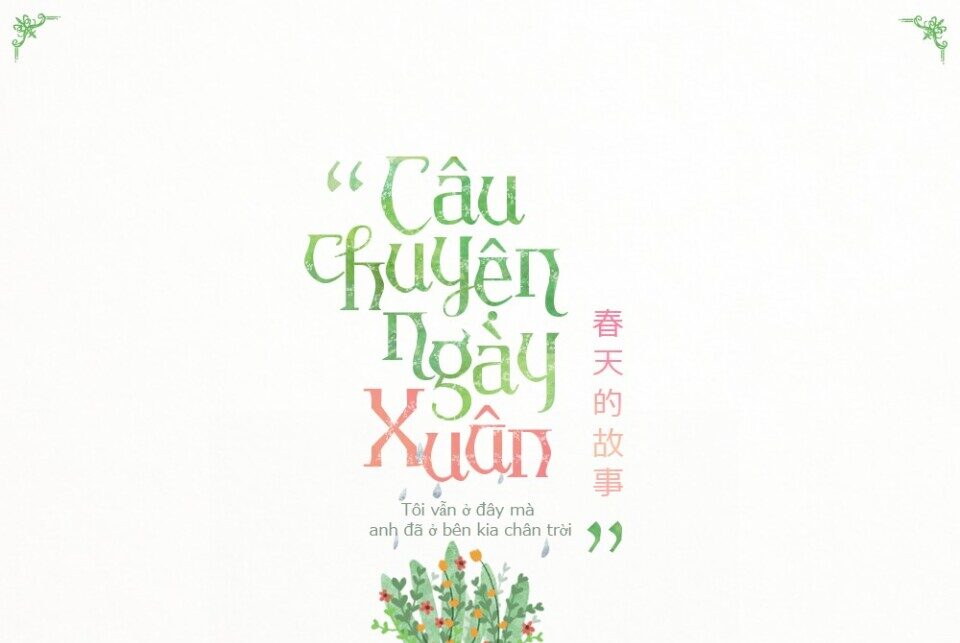
Font Việt hóa MTD Gambit Nouveau – Nét vẽ cổ điển đầy nghệ thuật
Giới thiệu về Font Việt hóa MTD Gambit Nouveau
Trong thế giới thiết kế đồ họa, việc tìm kiếm một bộ Font Miễn Phí mang đậm phong cách cổ điển nhưng vẫn đảm bảo tính thẩm mỹ cao luôn là ưu tiên hàng đầu. Font Việt hóa MTD Gambit Nouveau chính là một lựa chọn hoàn hảo như vậy. Đây là bộ phông chữ được lấy cảm hứng từ phong trào nghệ thuật Art Nouveau nổi tiếng, mang đến sự uyển chuyển, mềm mại trong từng đường nét. Việc sử dụng Font Việt hóa MTD Gambit Nouveau giúp các tác phẩm thiết kế trở nên sang trọng, lãng mạn và có chiều sâu văn hóa rõ rệt, đặc biệt phù hợp cho các dự án sáng tạo cần sự tinh tế.
Đặc điểm nổi bật của bộ font chữ này
Bộ phông chữ này gây ấn tượng mạnh mẽ nhờ cấu trúc chữ độc đáo, kết hợp giữa những đường cong uốn lượn và các chi tiết cách điệu tỉ mỉ. Khi trải nghiệm Font Việt hóa MTD Gambit Nouveau, người dùng sẽ cảm nhận được sự chỉn chu trong quá trình xử lý dấu tiếng Việt, giúp văn bản không bị lỗi font hay mất cân đối. Đây là công cụ đắc lực cho các bạn học sinh, sinh viên khi làm báo tường, thiết kế thiệp mời hoặc trang trí bìa sách trong môi trường học đường.
Ứng dụng thực tế của Font Việt hóa MTD Gambit Nouveau
Nhờ vẻ ngoài mang hơi hướng hoài cổ, bộ font này thường được ứng dụng rộng rãi trong thiết kế logo, bao bì sản phẩm cao cấp hoặc các ấn phẩm quảng cáo nghệ thuật. Ngoài ra, Font Việt hóa MTD Gambit Nouveau còn rất được ưa chuộng trong việc trình bày các trích dẫn văn học hoặc làm tiêu đề cho các video phong cách vintage trên mạng xã hội. Sự đa dạng trong cách thể hiện giúp nó trở thành một trong những phông chữ không thể thiếu trong bộ sưu tập của các designer chuyên nghiệp lẫn nghiệp dư tại Việt Nam.